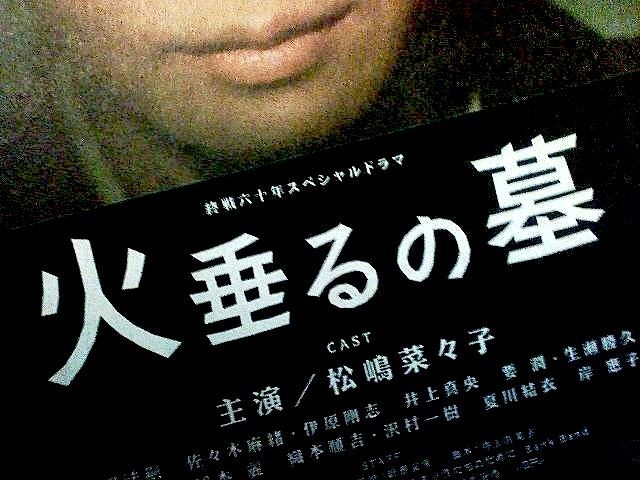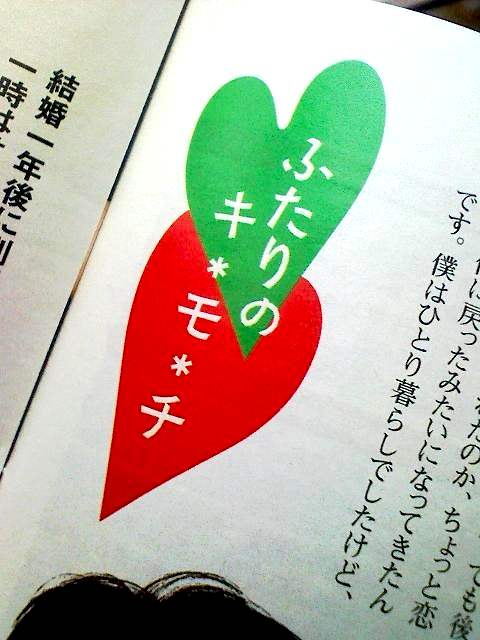
あられフォントのお試し版を使ってみて、とても素敵だと思ったのですが、
さとうゆたか  2010年2月1日(月) 15:37 [修正]
Mac用か、Win用か。
これはお使いのパソコンに合わせればいいので、迷いませんよね。
では、等幅か普通の物か…。
等幅フォントと普通の物の違いは、半角の英数字(ASCII文字)だけです。
無料版で違いを確認できますので、どちらかお好きな方を購入するのがイイと思います。
購入しなかった方の英数字を使いたくなったら、無料版フォントの英数字を使えばいいと思います…。
テレビCMから  さとうゆたか  2009年12月12日(土) 9:20
「冬のかに祭り」
スシローという回転寿司チェーンの広告。
これができたドラマCDです  デルタです  2009年9月22日(火) 22:40  HP
100%タイプラボ様のフォントを使用しています。
ここまでキレイにできるのは、タイプラボ様のおかげです。
ライブオン!のところはあられを使用。斜体化しています。
それ以外はすべてアニトを使用。
圧巻は右下のクレジット!こんな小さい字なのにツブれなし!
アニトは本文に使用しても読みやすく、優れた書体であると思います。
さとうゆたか  2009年9月23日(水) 7:17 [修正]
小さいですが  さとうゆたか  2009年7月24日(金) 15:39
書名:パリごはん
著者:雨宮塔子
発行:幻冬舎
心理学の本  さとうゆたか  2009年6月28日(日) 16:52
この心理学シリーズ全部に使われていました。
著者:福島 哲夫
発行:アスペクト
さとうゆたか  2009年6月28日(日) 16:53 [修正]
著者:福島 哲夫
発行:アスペクト
さとうゆたか  2009年6月28日(日) 16:53 [修正]
著者:福島 哲夫
発行:アスペクト
さとうゆたか  2009年6月28日(日) 16:54 [修正]
著者:福島 哲夫
発行:アスペクト
さとうゆたか  2009年6月28日(日) 16:54 [修正]
著者:福島 哲夫
発行:アスペクト
さとうゆたか  2009年6月28日(日) 16:57 [修正]
著者:福島 哲夫
発行:アスペクト
漫画の次号予告  さとうゆたか  2009年6月17日(水) 17:03
女性向けの漫画雑誌です。
浦沢直樹×手塚治虫  さとうゆたか  2009年3月5日(木) 16:40  HP
ビッグコミックオリジナルという漫画雑誌に連載されている「プルートウ」。
最後のページに載せられている次号の告知。
「あられ」の無料サンプル版「あられ-教漢」はサポート対象外だと思いますが、一つ気になったのでここに書かせていただきます。
「あられ-教漢」は、どうして教育漢字以外の文字が空白ではなく□になっているのですか?
「あられ-等幅教漢」は、特にそのようなものはありませんでした。
さとうゆたか  2009年3月5日(木) 7:51  HP [修正]
無料頒布あられのページ冒頭に記してあるように、
「あられ-教漢」が作成されたのは2001年。
「あられ-等幅教漢」が作成されたのは2006年。
たぶん作成したアプリケーションのバージョンの違い、または当方の作成方法の違いが影響しているのだと思います。
文庫本の表紙  さとうゆたか  2009年1月12日(月) 22:12
書名:城のなかの人
著者:星新一
発行:角川書店
城の文字に手をいれて、点の部分が丸に変更されていますが。
だんぜんお得な!飲み放題  さとうゆたか  2008年12月5日(金) 17:10
亀戸駅近くの居酒屋の店頭で。